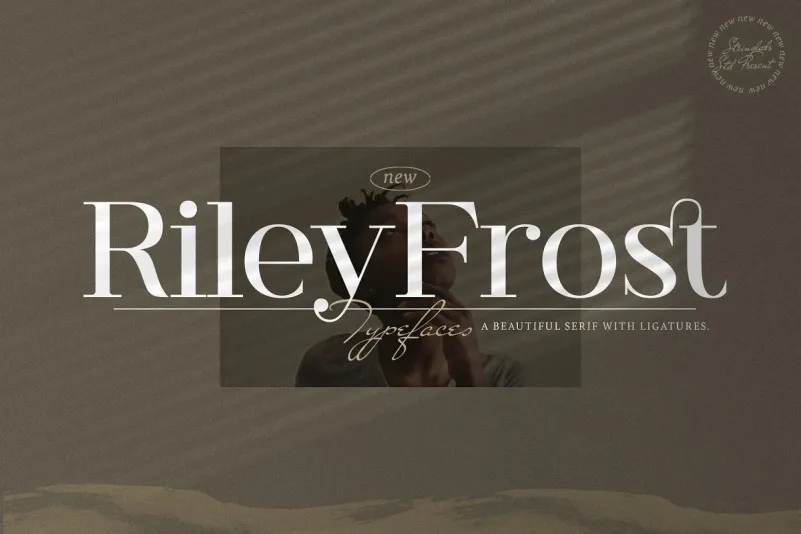
Riley Frost Serif Font – Download Grátis
Afonte ‘Riley Frost Serif Font’ é uma elegante escolha para projetos que exigem um toque clássico e sofisticado. Desenvolvida pela StringLabs na plataforma de design 99designs, ela oferece um sabor autêntico ao seu design com um toque especial de ligação de letras extra. Seu estilo serif é tanto uma bênção quanto um desafio para os designers, pois pode ser facilmente combinada em diversos projetos, desde publicações profissionais até trabalhos gráficos criativos. O uso desta fonte não só melhorará a legibilidade dos seus textos, mas também dará seu projeto aquela leveza e sofisticação que tornam as ideias singulares se destacarem na pauta de projetos. A ‘Riley Frost Serif Font’ é um presente inesperado para os designers interessados em adicionar um toque de elegância ao seu trabalho. Com suas formas precisas, esta fonte oferece um conjunto vasto e poderoso que pode ser usada de diversas maneiras, dependendo do seu propósito e dos projetos específicos. Em uma era repleta de gráficos digitais e formatos modernos, a ‘Riley Frost Serif Font’ torna-se uma escolha inteligente para aqueles procurando por um contraponto reconfortante e confiável, que complementará sua visão visual sem deixar de lado.